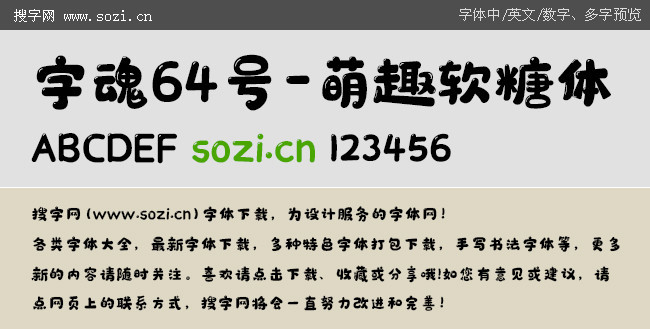
字魂64號(hào)-萌趣軟糖體
搜字網(wǎng)提供一款字魂64號(hào)-萌趣軟糖體中文字體下載,該字體是一款卡通可愛創(chuàng)意體字體,該字體包含6763個(gè)中文、字母、 符號(hào)和數(shù)字,具有童真、活潑、動(dòng)漫、有趣 的風(fēng)格,可以滿足您設(shè)計(jì)上的各種需求,該字體主要用于書籍、報(bào)紙、游戲、動(dòng)漫 等場(chǎng)景。